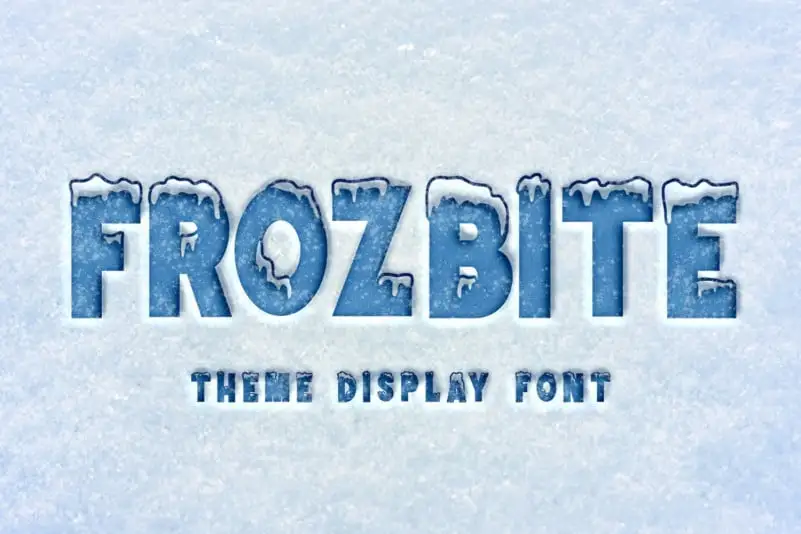
A FROZBITE Display Font é uma elegante escolha para qualquer evento noturno ou festa decoração. Inspirada no horror moderno, ela se destaca como um tipo de exibição bold e decorativo perfeito para a celebração do Halloween, Natal ou Ano Novo. Seu design robusto e repleto de detalhes é ideal para criar atmosferas assustadoras em qualquer projeto gráfico. Esta fonte deixa sua marca com seu impacto visual forte, garantindo que qualquer texto decorado seja o centro das atenções. Com uma paleta vibrante, esta FROZBITE se torna não apenas um adorno, mas também um componente fundamental para estabelecer a atmosfera do evento. Sua elegância e agressividade combinam harmoniosamente, criando uma experiência visual intensiva que nunca poderia ser ignorada em qualquer projeto decorativo.